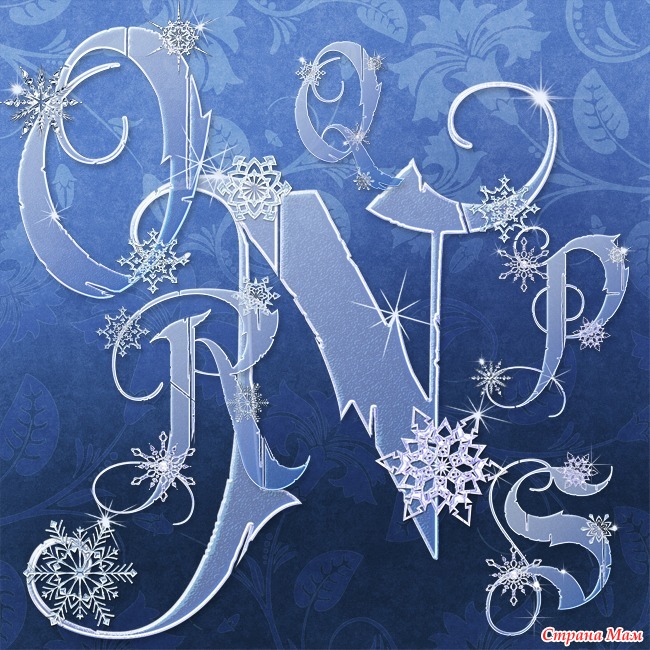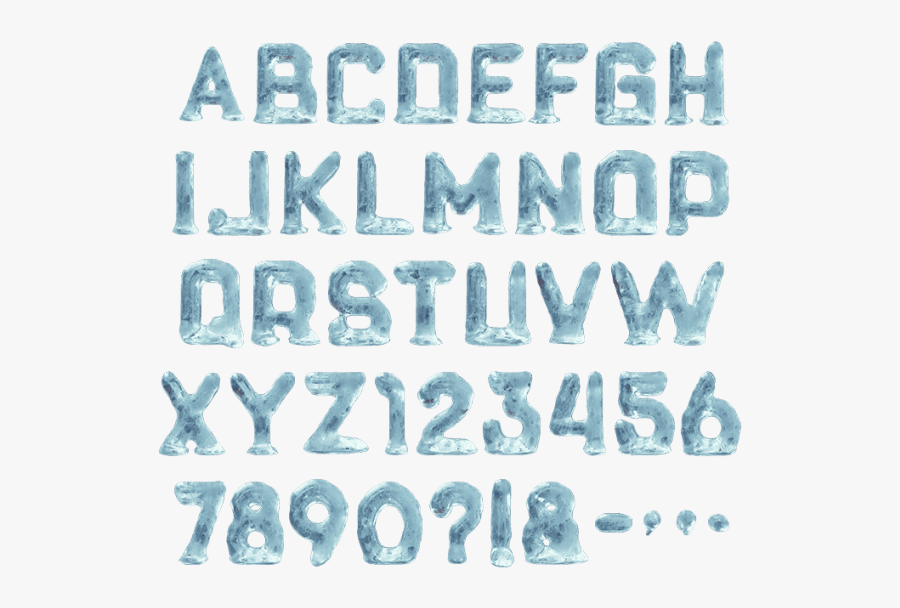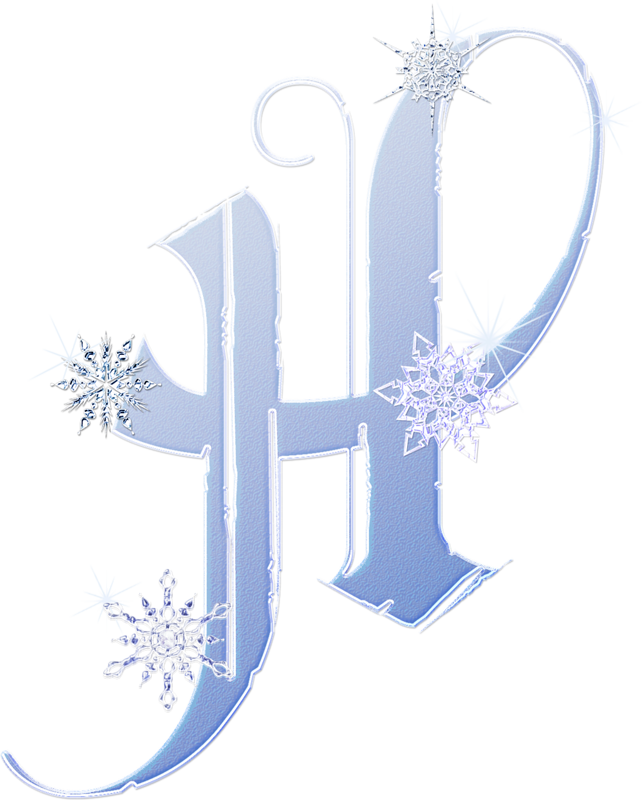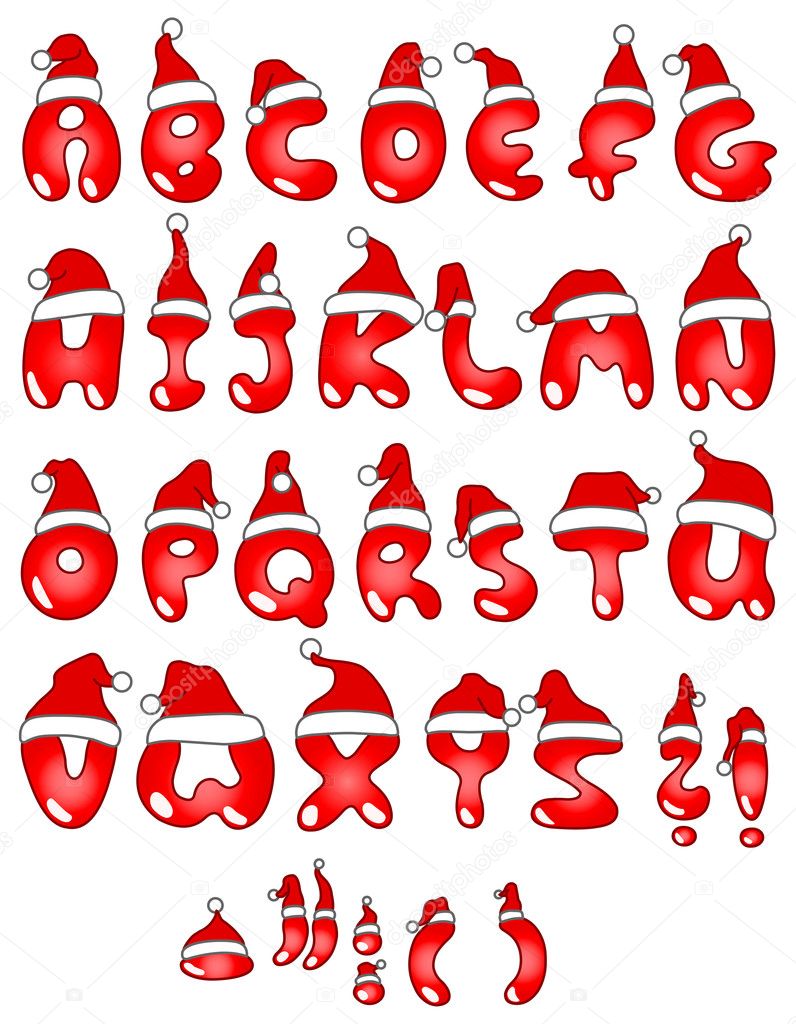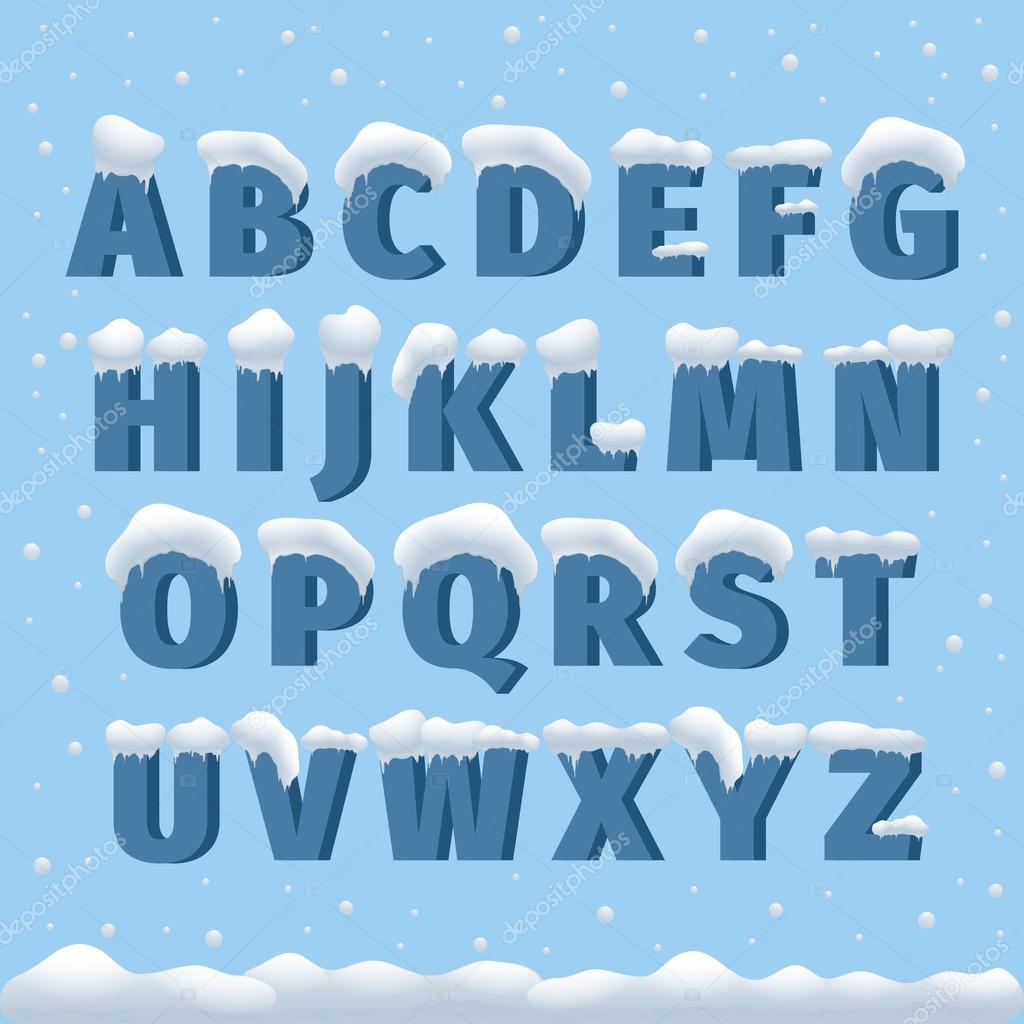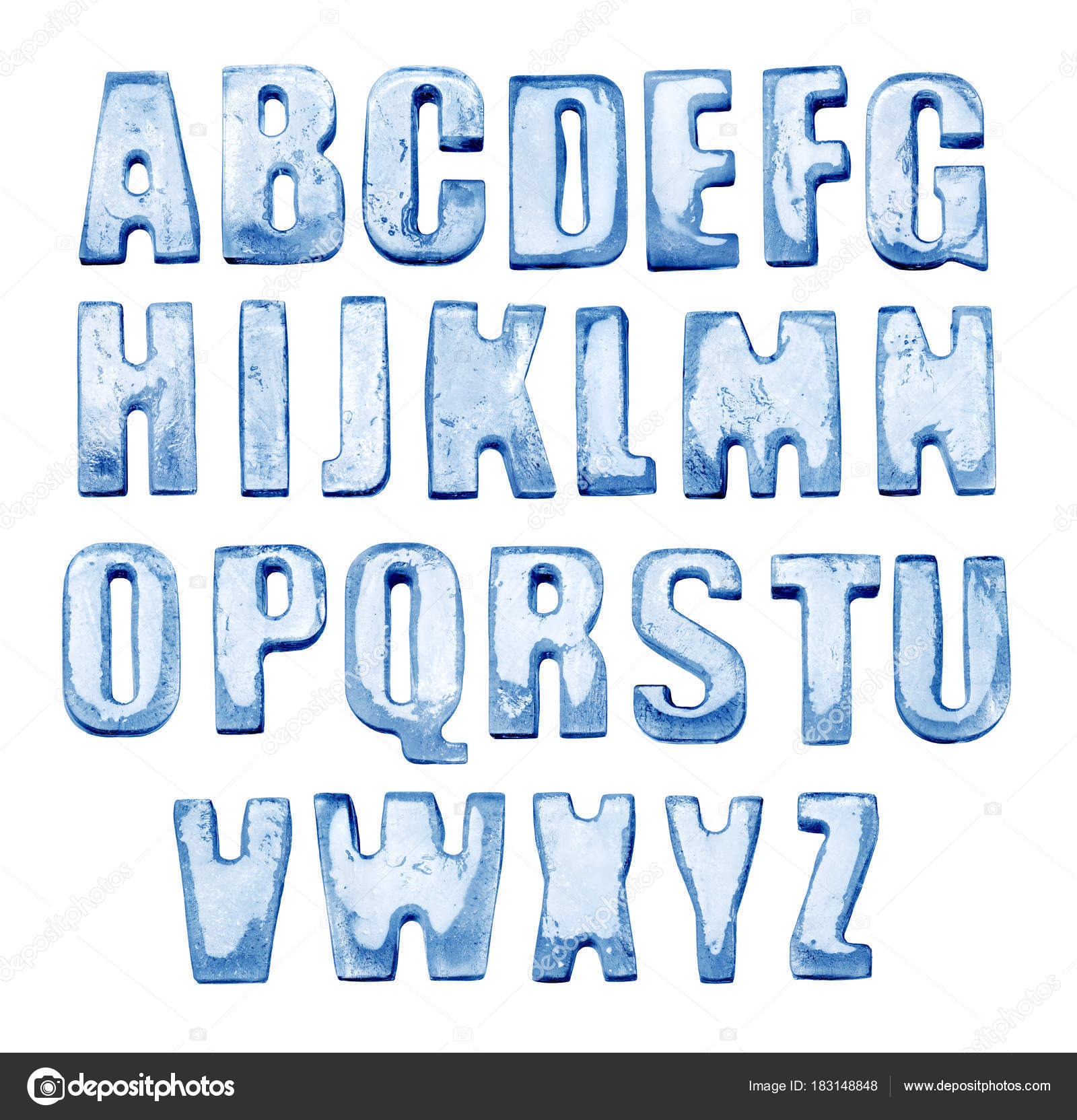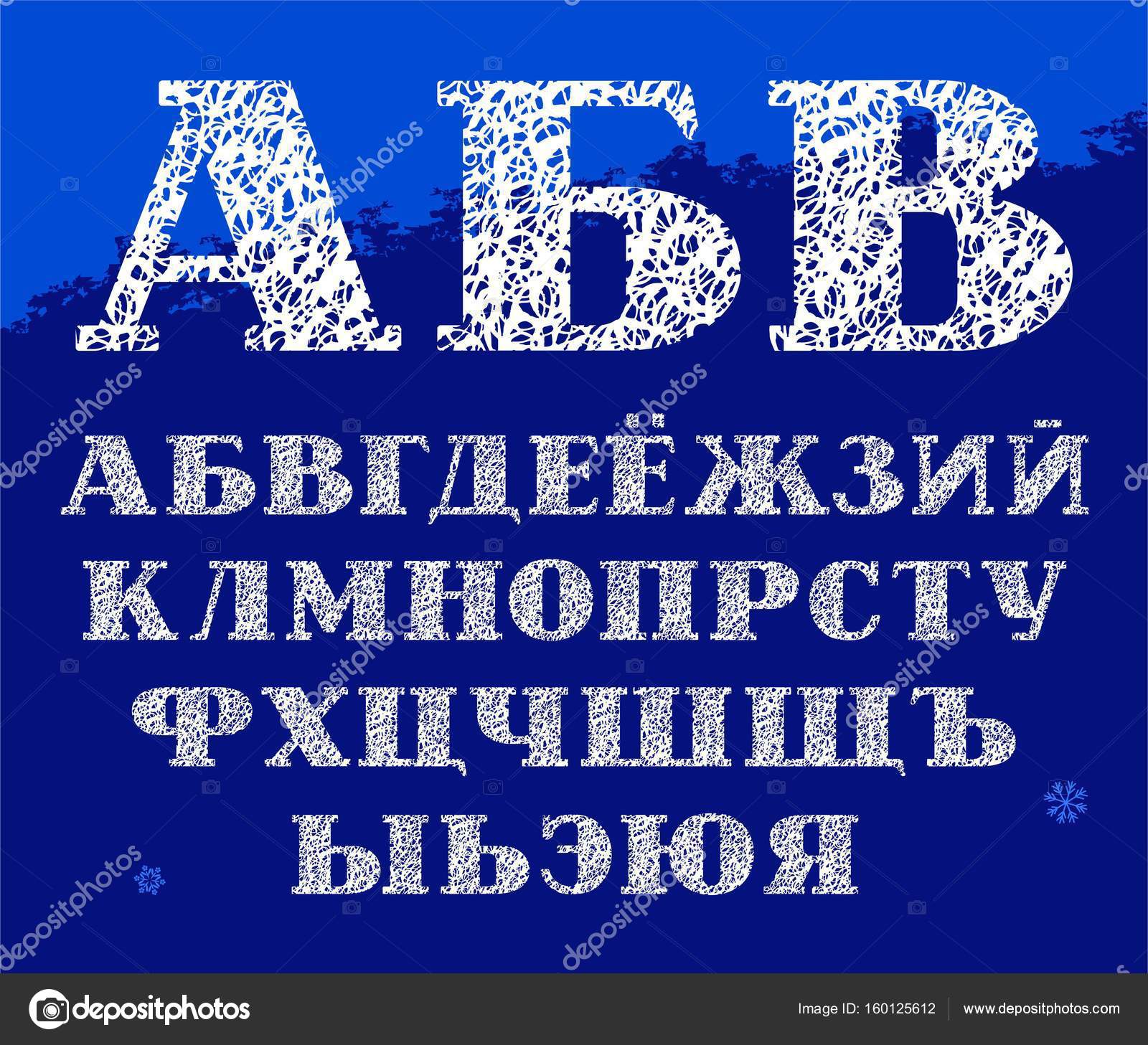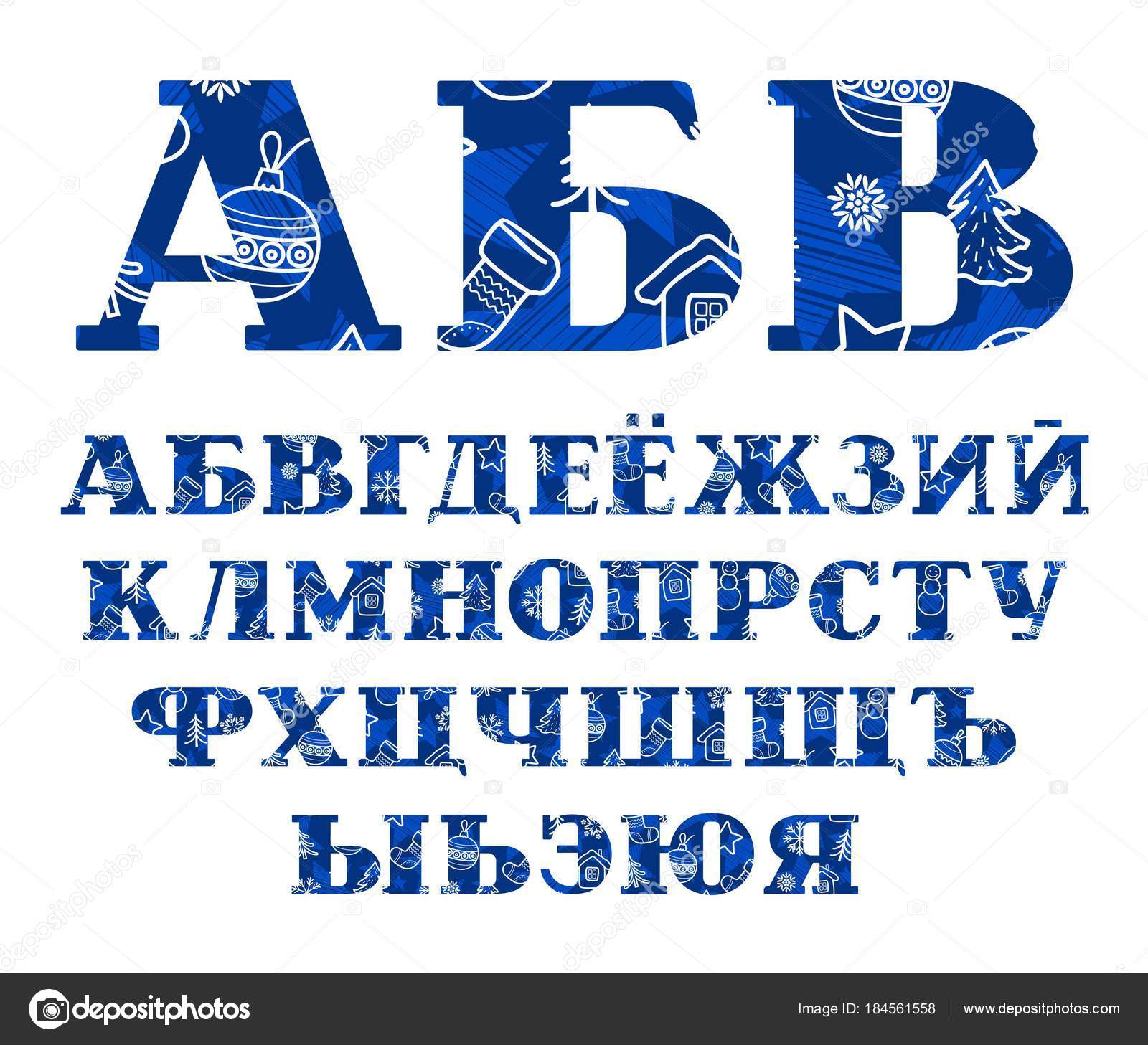
Зимний русский шрифт: Новогодние шрифты, скачать бесплатно (русские рождественские шрифты на Facefont)
Снежные зимние шрифты для фотошопа (45 оригинальных шрифтов)
По случаю наступившей зимы мы решили подготовить тематическую заметку про зимние шрифты. Года два назад в Дизайн Мании уже были публикации о новогодних и рождественских шрифтах, однако там собраны далеко не все интересные варианты + за пару лет появились новые работы. Уверены, в статье ниже найдете парочку полезных решений. В свою очередь мы проследим чтобы в данной и предыдущих подборках объекты не повторялись.
В посте будет три небольших подраздела — ледяные, снежные и зимние шрифты. Что касается самих материалов, то реализация во многих случаях похожа, в качестве декора для букв выступают снежинки, снег, сосульки и т.п. Есть работы, где вместо букв найдете разные тематические объекты — елки, новогодние игрушки и всякое такое. Для некоторых шрифтов важно подобрать правильный цвет, который бы заставил их выглядеть максимально по-зимнему.
Ледяные шрифты
Основной «атрибут» ледяных шрифтов для фотошопа — это конечно сосульки, которые встречаются в большинстве вариантов ниже. Есть здесь как более-менее обычные так и декоративные фонты. Неплохо выглядят готические Gothic и Plymouth Rock Snowd.
101 Arctic Blast
Ice Sticks
Ice Caps
Modius Frigid
Generic Uncials Snowcapped
Plymouth Rock Snowd
Gothic Winter
Freezer Font
Winter Ice
Ice And Snow
Frostyholiday
Ice Cold
Снежный шрифт
Снег на буквах — вообще классика зимних шрифтов. Не смотря на то, что многие реализации похожи, есть здесь и свои уникальные нюансы. Вам нужно просмотреть все решения и подобрать то оформление, которое больше всего подходит.
Snow For Santa
Winter Flakes
Winter Decor
Snowfall
Chilled
Neige
PW Happy Christmas
LMS Let It Snow
RYP Snowflake 2 font
Snaps Taste Christmas Font
StarsPROMO
Зимние шрифты
В последнем разделе представлены разные зимние шрифты для фотошопа: есть тут и варианты со снегом, и рукописные, и декоративные. Прикольно смотрится Christmas Jumper, который используется для узоров на зимних свитерах. Merry Christmas отлично подойдет для оформления праздничных открыток. Cartoon Blocks Christmas и Maple3 Cartoon Font словно созданы для мультяшной/детской тематики.
CF Tuques
Igloo Laser
Snowtop Caps
Snow House
Krystal
Winter Night
Snow Traces
CF Grand Nord
Christmas Jumper
Merry Christmas
Snowmen
Icebox Art
I Love Christmas
Ornamental Eric
Christmas Tree
It’s beginning To Look A Lot Lik
Cartoon Blocks Christmas
Maple3 Cartoon Font
Bodiemf Holly
Christbaumkugeln
CF Snowball
Snowinter
Pwjoyeuxnoel Font
Кстати, в сети можно найти вектор в виде зимних шрифтов, что также пригодится для создания иллюстраций. Ниже увидите примеры парочки соответствующих реализаций.
Ice Font
Snowy Vector Font Type
Ice Type Vector Font